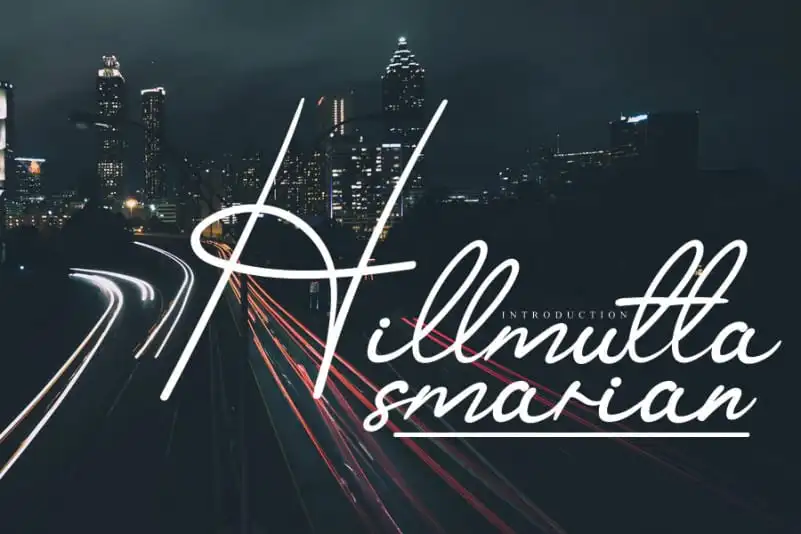
Hillmutta Handwritten Font – Fonte Grátis
Hillmutta Handwritten Font – Download Grátis
Hillmutta Handwritten Font
Hillmutta Handwritten Font é uma elegante fonte escrita a mão que transmite tranquilidade com seu estilo fluido e contemporâneo. Esta fonte foi criada para projetos especiais, onde você pode capturar sua essência única através da letra de mãos. Perfeita tanto para trabalhos diários quanto para projetos de arte mais elaborados, Hillmutta oferece um toque distintivo que mantém seu design versátil e contemporâneo ao longo do tempo. Com uma aparência suave e perfeitamente adaptada aos olhos modernos, a fonte é ideal tanto para criar designs impressionantes quanto para dar identidade a seus trabalhos. Seu estilo único é inconfundível e não demora muito para se tornar sua escolha favorita, ajudando-a a destacar em qualquer projeto de arte visual.